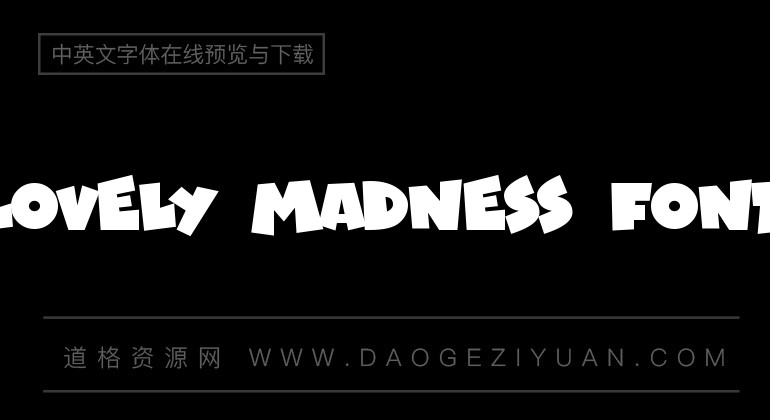
Lovely Madness Font
Lovely Madness Font是一种装饰性的手写字体,由Silvia Otte设计。该字体的特点是其独特的笔画,既可爱又疯狂,带有一些有机风格的元素。Lovely Madness Font可用于各种项目,如海报、广告、包装、卡片、书籍封面等。其设计灵感来源于手工书写,有些字母看起来像是用毛笔书写的。如果你想要设计一个有趣、温馨、个性化的项目,Lovely Madness Font可能是一个不错的选择。
Lovely Madness Font是一款非常不错的手写艺术字体,具有很好的视觉感,适合于文化类的宣传设计、商业类品牌的广告和产品包装设计以及个性化文字排版等较多场景。